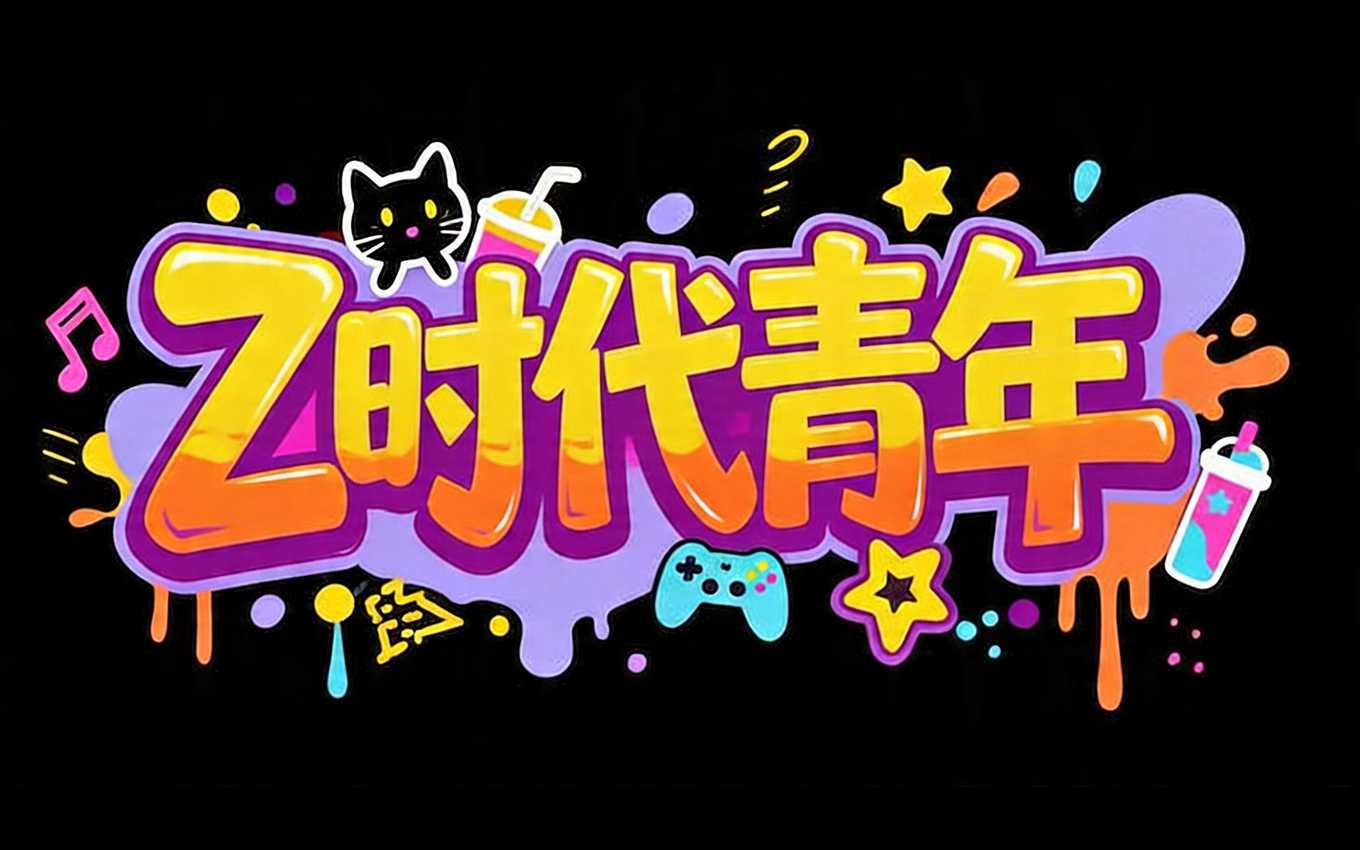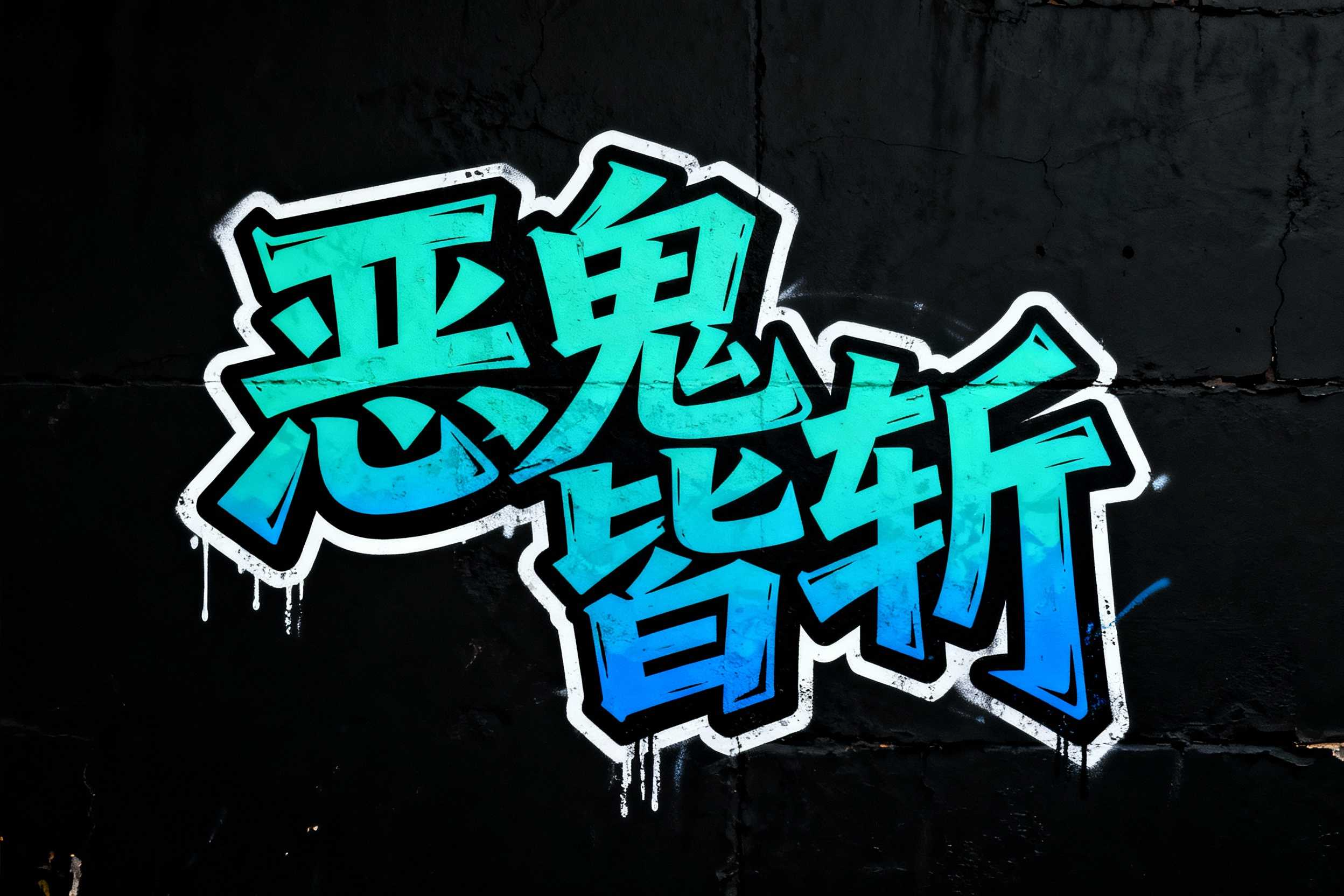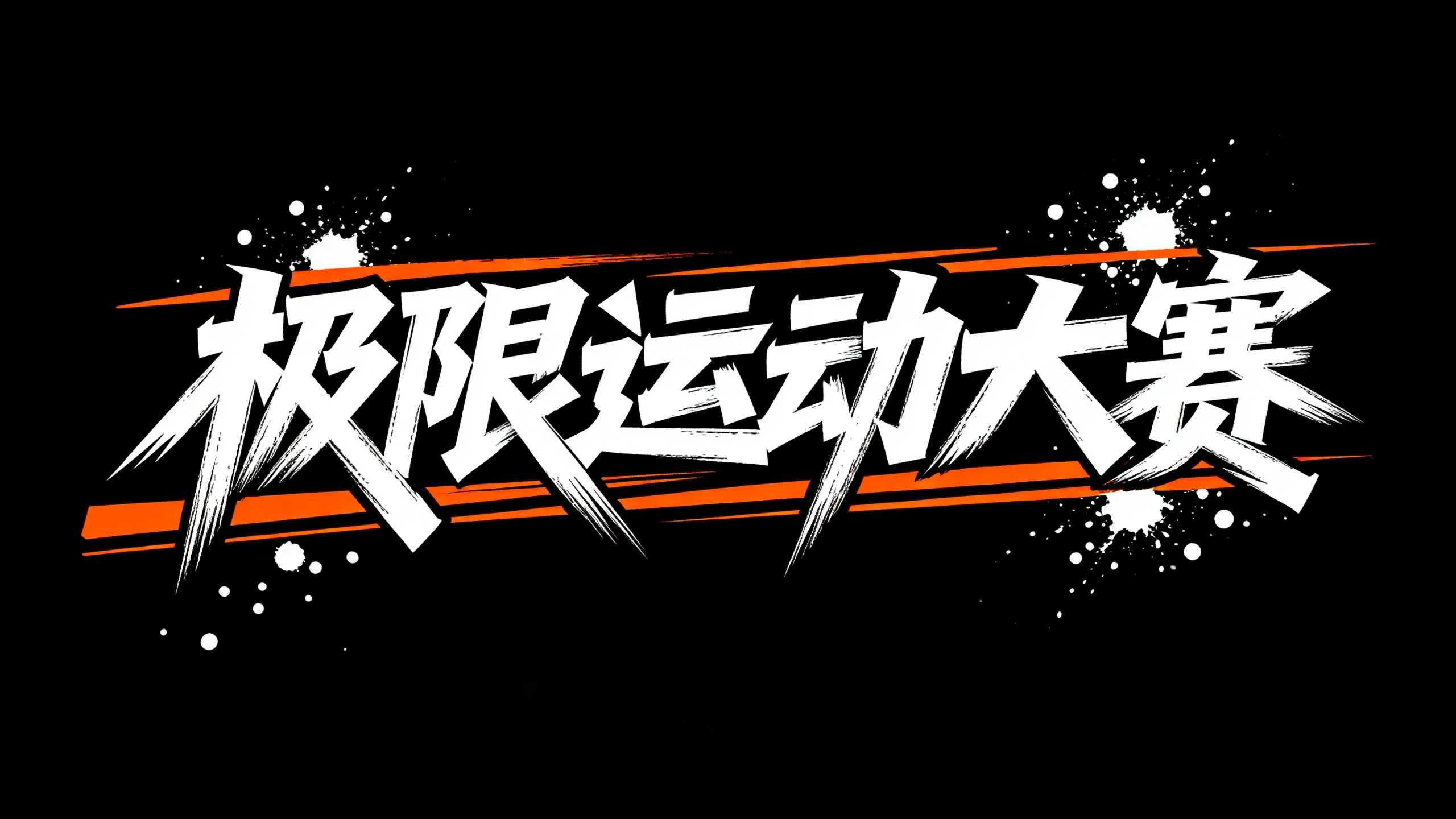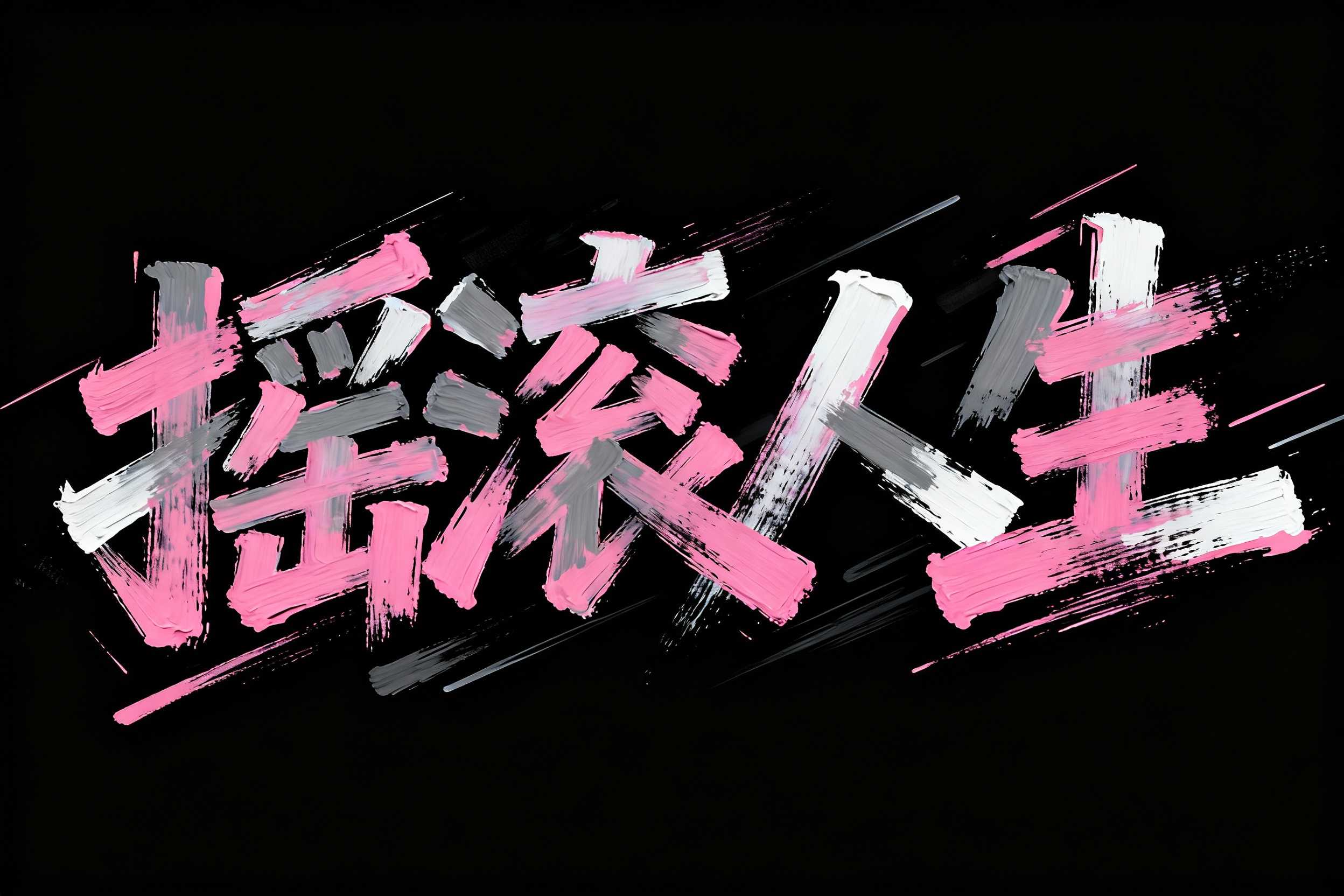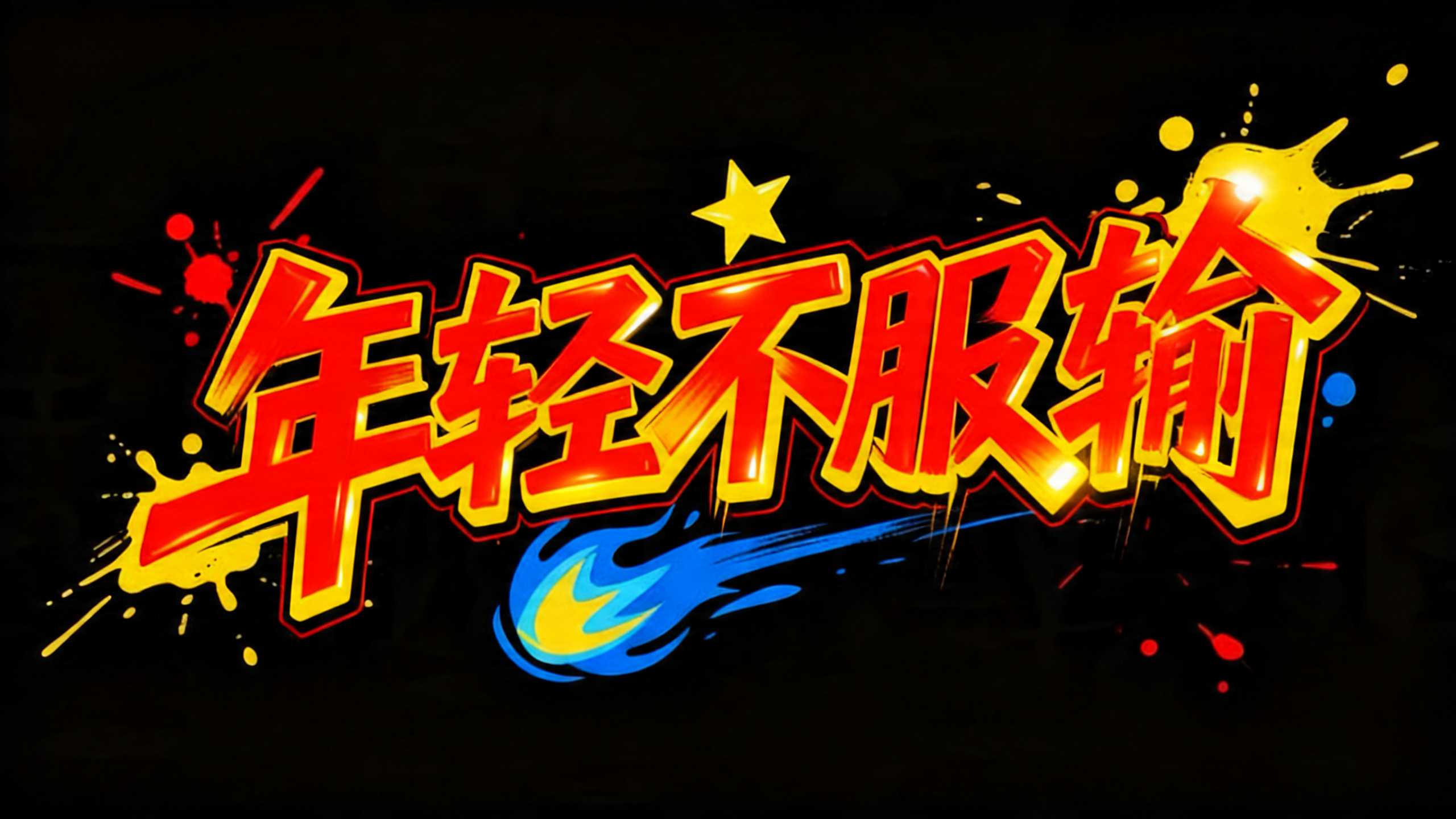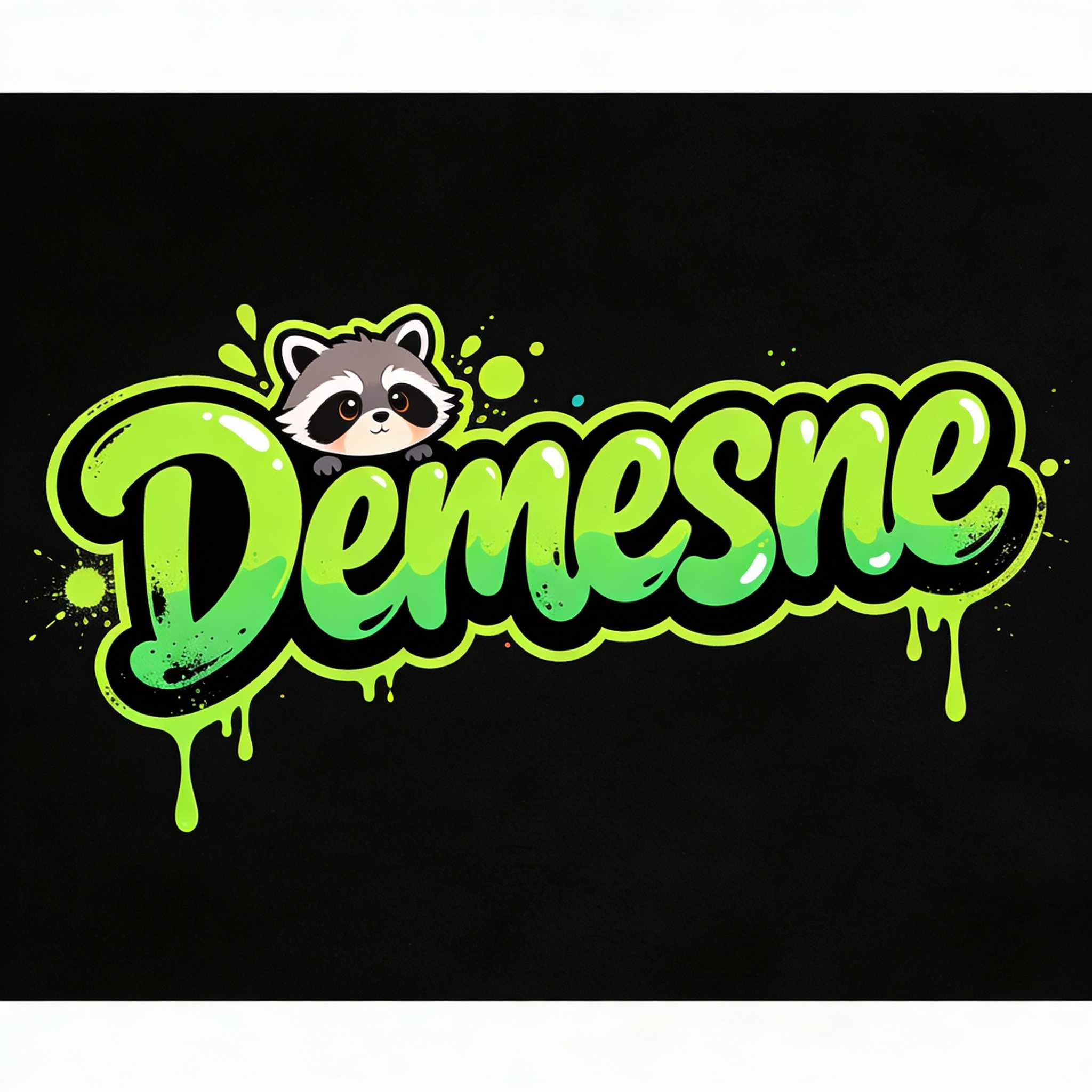
6款街头艺术风格AI字体:让字体秒变潮流视觉焦点
从嘻哈文化的张扬表达,到运动赛场的激情释放,再到亚文化圈层的个性展示,街头风格字体正以前所未有的活力渗透到各类设计场景中。
本文将深度解析6款极具代表性的街头艺术风格AI字体,揭秘如何零基础设计出专业级的涂鸦风视觉效果。
「Z时代青年」:波普漫画风
视觉特征剖析:这款字体完美融合了美式卡通漫画与日系街头涂鸦的双重基因。高饱和度的明黄与电光紫形成强烈的视觉对冲,字形采用夸张的膨胀比例,边缘点缀着游戏手柄、黑猫、星星与喷溅墨点。这种漫画风与涂鸦风的跨界组合,精准捕捉了Z世代"虚拟与现实交织"的生活状态。
场景应用与关键词植入:社团招生宣传与兴趣班:针对街舞社、滑板社、电竞社等青年文化社团的招新海报标题字体,能瞬间点燃报名热情。游戏美术与周边设计:作为潮玩品牌、联名款T恤的图案,或二次元手游的开屏特效文字,强化年轻化定位。社交媒体传播:在小红书、抖音等平台的海报设计中,这种活力四射的风格极易引发自发传播,形成话题裂变。
「恶鬼皆斩」:硬核美式美学
视觉特征剖析:纯粹的纽约地铁涂鸦风格,锋利的棱角与流畅的曲线在三维空间中扭曲交错。青绿色渐变填充配合粗犷的黑色轮廓线,辅以模拟喷漆罐滴落的白色痕迹,构建出强烈的复古街头质感。这种被称为"Tag"的签名式字体,是街头艺术最原始的基因表达。
场景应用与关键词植入:艺术展与文创空间:极限运动品牌快闪店、地下艺术展的墙面装饰与导视系统,营造沉浸式美式风格氛围。体育竞技赛事:街球联赛、跑酷锦标赛的场地围挡与选手出场海报设计,传递硬核竞技精神。影视与短视频:动作片、悬疑剧的片头字幕,或国潮短视频的章节分隔符,增强画面的叙事张力。
「年轻不服输」:动感速度风
视觉特征剖析:这款字体将街头涂鸦与运动图形设计完美融合。倾斜的字形结构自带向前冲刺的动势,红色主调配以火焰般的黄色外发光,底部拖曳的蓝色流星轨迹强化了速度感。每一笔都仿佛在燃烧,将热情与不服输的斗志可视化。
场景应用与关键词植入:体育竞技赛事海报:大学生篮球赛、城市马拉松的主视觉字体,作为海报标题字体能瞬间调动观众情绪。校园宣传与毕业季:毕业季励志海报、学生会换届宣传的社团招生宣传物料,展现青春锋芒。极限运动推广:滑板、BMX小轮车等运动品牌的包装设计与赛事墙画设计,契合挑战极限的品牌内核。
「摇滚人生」:狂野笔刷风
视觉特征剖析:摒弃规整的几何结构,完全回归手绘本质。粉色与金属银的交替涂抹模拟了丙烯颜料在粗糙画布上的堆叠效果,飞白的笔触与倾斜的辅助线条营造出即兴创作的疯狂感。这种怀旧又前卫的风格,是摇滚乐自由精神的完美视觉转译。
场景应用与关键词植入:音乐节与Livehouse:独立音乐节的舞台背景海报设计,乐队专辑封面与巡演海报标题字体。艺术教育培训:吉他、架子鼓等兴趣班的宣传册与体验课邀约海报设计,吸引追求个性的青少年群体。潮牌服装与文创:摇滚主题帆布包、黑胶唱片周边、乐队联名款包装设计的核心视觉元素。
「Demesne」:甜酷泡泡体
视觉特征剖析:这款字体展现了街头风格的柔软一面。果冻般半透明的绿色渐变,配合不断滴落的荧光绿描边,营造出糖果甜食般的诱人质感。顶部探出头的卡通浣熊打破了文字的静态平衡,这种"甜酷"(Sweet & Cool)风格正是当下亚文化圈层的新宠。
场景应用与关键词植入:IP形象与周边开发:萌系游戏美术的角色名展示,潮玩盲盒系列的包装盒印刷与吊牌设计。美妆与轻食品牌:面向Z世代的饮品店、低糖零食的包装设计与社交媒体种草图,复古又俏皮。亲子与青少年活动:少儿街舞夏令营、动漫嘉年华的海报设计,降低街头风格的攻击性,增加亲和力。
「极限运动大赛」:力量破碎风
视觉特征剖析:字形如利刃般锋利,笔画末端的破碎效果模拟了极限运动中混凝土、冰块或玻璃的炸裂瞬间。纯白主调与警示橙的横条纹形成高对比度,配合飞溅的墨点与速度线,构建出极具侵略性的特效文字效果。
场景应用与关键词植入:大型体育赛事KV:城市极限运动公开赛的主视觉字体与主KV、颁奖舞台的会议大屏幕动态背景。户外运动装备:滑雪板、滑板底部的贴纸设计,冲锋衣、护具的印花图案与电商详情页海报设计。青年文化节日:城市青年文化节、创意市集的户外墙画设计与指引系统,强化活动的先锋属性。
字由AI字体,让街头艺术触手可及
上述6款风格迥异却同样震撼的街头艺术字体,如果采用传统设计流程,需要设计师熟练掌握Adobe Illustrator的钢笔工具、各种涂鸦笔刷的调试,以及复杂的三维材质渲染。对于社团招生宣传的学生干部、缺乏设计基础的兴趣班老师,或是急需产出视觉物料的市场专员而言,这构成了极高的准入门槛。
但是,字由AI字体却可以让你零基础完成创作:
平台汇聚了大量具有强烈艺术感的AI字体模板,使用者无需编写复杂的AI提示词,更不需要额外学习Photoshop或AI工具技能,只需在字由客户端输入核心文案(如"年轻不服输"或"摇滚人生"),即可一键生成同款,直接应用于游戏美术、包装设计、艺术展等不同媒介。街头艺术不再是少数专业设计师的专属领地。